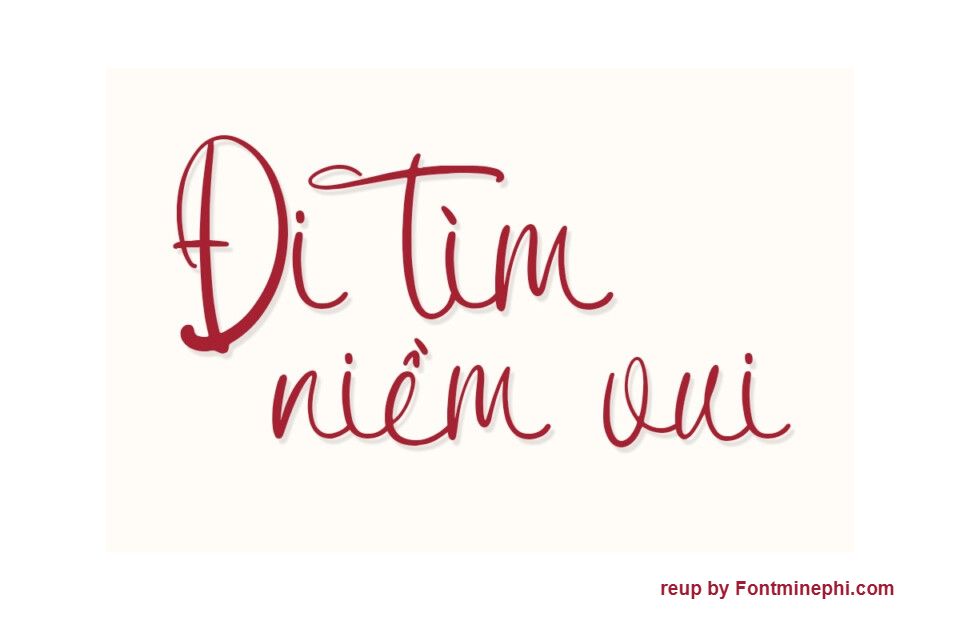
Font Việt hóa 1FTV VIP Sweet Fruity
Font Việt hóa 1FTV VIP Sweet Fruity là bộ phông chữ nghệ thuật tuyệt đẹp được tạo ra nhằm đáp ứng nhu cầu thiết kế đồ họa ngày càng đa dạng và đòi hỏi tính sáng tạo cao. Với nét vẽ ngộ nghĩnh, mềm mại cùng cảm hứng từ sự tươi mát của trái cây mùa hè, đây sẽ là công cụ đắc lực nâng tầm diện mạo cho các thương hiệu trà sữa, bánh ngọt, sản phẩm dành cho trẻ em hay các ấn phẩm truyền thông mạng xã hội. Bộ phông đã được Việt hóa hoàn chỉnh, chuẩn hóa toàn bộ dấu câu giúp các nhà thiết kế tự tin thực hiện mọi ý tưởng mà không lo lỗi hiển thị.
Font Việt hóa 1FTV VIP Sweet Fruity – Lựa Chọn Hoàn Hảo Cho Thiết Kế Ngọt Ngào Và Sáng Tạo
Trong thế giới thiết kế đồ họa hiện đại, việc lựa chọn phông chữ (typography) đóng vai trò then chốt trong việc định hình cảm xúc và phong cách của sản phẩm. Một bộ font phù hợp không chỉ giúp truyền tải nội dung một cách rõ ràng mà còn là chìa khóa thu hút sự chú ý của khách hàng ngay từ cái nhìn đầu tiên. Font Việt hóa 1FTV VIP Sweet Fruity chính là sự kết hợp hoàn hảo giữa tính thẩm mỹ hiện đại và sự gần gũi, mang lại trải nghiệm thị giác sống động và tràn đầy năng lượng cho mọi tác phẩm.
1. Nét chữ mềm mại, phong cách đáng yêu và tràn đầy năng lượng
Điểm ấn tượng đầu tiên của font Việt hóa 1FTV VIP Sweet Fruity nằm ở kiểu dáng tròn trịa, uốn lượn tự nhiên mang đậm hơi thở của các nét vẽ thủ công. Các đường nét được gọt giũa tỉ mỉ, không quá cứng nhắc nhưng cũng không làm mất đi tính cân đối của tổng thể cấu trúc chữ.
• Tạo cảm giác thân thiện, vui tươi và gần gũi cho người xem ngay từ cái nhìn đầu tiên.
• Thích hợp cho các chủ đề thiết kế hướng đến giới trẻ, trẻ em, ẩm thực ngọt, trà sữa, hoa quả tươi và các sự kiện mùa hè năng động.
• Độ dày nét chữ (weight) chuẩn xác, giúp tiêu đề luôn nổi bật trên nhiều nền màu sắc và hình ảnh phức tạp.
2. Việt hóa trọn bộ chuẩn chỉnh, hỗ trợ tối đa Tiếng Việt
Nhiều bộ font nước ngoài dù đẹp mắt nhưng lại gặp hạn chế lớn khi sử dụng tại Việt Nam do thiếu hệ thống dấu tiếng Việt hoặc dấu bị lệch, làm mất đi tính thẩm mỹ chung. Font Việt hóa 1FTV VIP Sweet Fruity đã giải quyết hoàn toàn bài toán này bằng cách chỉnh sửa tỉ mỉ từng ký tự có dấu.
Hệ thống các dấu sắc, huyền, hỏi, ngã, nặng cũng như các chữ cái đặc thù như Ă, Â, Đ, Ê, Ô, Ơ, Ư đều được canh chỉnh khoảng cách và độ cao một cách hoàn hảo. Nhờ đó, văn bản khi gõ bằng tiếng Việt vẫn giữ nguyên được vẻ đẹp thanh thoát, tự nhiên của bản gốc mà không gặp bất kỳ sự cố vỡ nét hay sai lệch tỉ lệ nào.
3. Tính ứng dụng đa dạng trong nhiều lĩnh vực thiết kế đồ họa
Không chỉ giới hạn trong một khuôn khổ nhất định, 1FTV VIP Sweet Fruity sở hữu tính linh hoạt cực cao, đáp ứng xuất sắc nhu cầu của nhiều ngành nghề và sản phẩm sáng tạo khác nhau:
1. Thiết kế nhận diện thương hiệu & bao bì: Bộ font rất phù hợp để làm logo, slogan, nhãn mác cho các chuỗi cửa hàng bánh kem, quán trà sữa, cửa hàng trái cây nhập khẩu, mỹ phẩm thiên nhiên hay các dòng sản phẩm cho mẹ và bé.
2. Ấn phẩm truyền thông & Quảng cáo: Thích hợp để thiết kế banner, poster, standee, voucher khuyến mãi, bài đăng Facebook, Instagram, TikTok hay thumbnail YouTube cần sự bắt mắt và cuốn hút.
3. Thiết kế thiệp & Quà tặng: Nét chữ dễ thương giúp tạo nên những chiếc thiệp sinh nhật, thiệp mừng, bìa sổ tay, sticker hay áo thun vô cùng độc đáo và cá tính.
5. Bộ ký tự mở rộng giúp tối ưu hóa khả năng sáng tạo
Bên cạnh các ký tự chữ cái và chữ số tiêu chuẩn, bộ phông chữ này còn tích hợp nhiều ký tự đặc biệt, biểu tượng trang trí cùng các tính năng OpenType nâng cao. Designer có thể dễ dàng biến tấu các con chữ, tạo nên những đường nối nghệ thuật (ligatures) hay các nét uốn biến thể (stylistic alternates) để sản phẩm của mình trở nên khác biệt, độc đáo và mang đậm dấu ấn cá nhân.
Font Việt hóa 1FTV VIP Sweet Fruity không chỉ là một công cụ chữ viết thông thường mà còn là nguồn cảm hứng sáng tạo vô tận cho cộng đồng nhà thiết kế và sáng tạo nội dung. Với sự kết hợp tài tình giữa nét chữ ngộ nghĩnh, sự tỉ mỉ trong khâu Việt hóa và tính ứng dụng đa dạng, bộ font này chắc chắn sẽ là một mảnh ghép không thể thiếu trong bộ sưu tập phông chữ chuyên nghiệp của bạn.